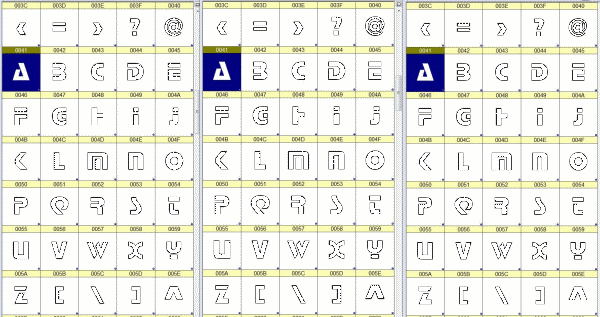
Auch euer Designer braucht, wenn er jetzt diese Schrift für weitere Aufträge (nicht nur für Euch) nutzt nicht jedes mal eine neue Lizenz.
Danke Euch allen für die ausführlichen Antworten - eine tolle Community! :-)
Es handelt sich konkret um die Schrift "Stop SCD". Ich habe ein wenig im Internet gesucht und die auch bei etlichen Logos anderer Firmen gefunden (wir sind eine Spedition). Das beruhigt schon etwas.
Lustigerweise gab es diese Schrift auch auf zig (englischsprachigen) Seiten zum Download "for free" - das kann doch nicht legal sein, oder ?
Naja, jedenfalls ist mir die Sache nun klarer. Das Logo ist übrigens eine Vektorgrafik im SVG-Format, die Zeichen sind als Pfade eingebunden.
Da es sich um eine reine Schmuckschrift handelt, hatte ich nicht vor, damit Rechnungen zu tippen. :-) Aber wir werden doch eine Lizenz für die Schrift kaufen (direkt bei URW++) , denn eventuell machen wir mal selbst einen Flyer oder so.
oder die Tatsache, dass Klein- und Großbuchstaben nahezu identisch sind
Sie SIND Identisch, die Stop hat keine Kleinbuchstaben, es ist eine reine Versalschrift. Und es war nicht Startreck, die mit der Stop kam, sondern Kampfstern Galaktica von 1978/79.
Und ja, es ist immer nur als Displayschrift gedacht gewesen.
Richtig bekannt ist sie übriens durch die Letraset-Abreibebögen geworden, da hatte ich die als erste gesehen.